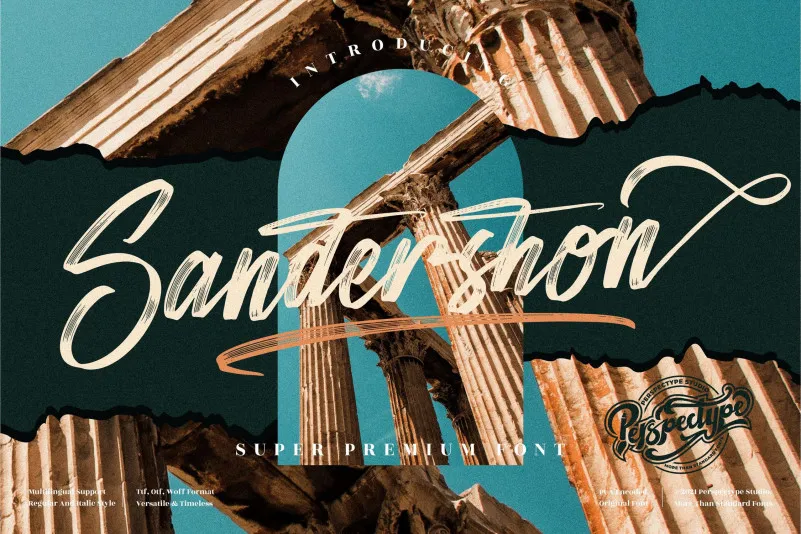
Sandershon Font – Download Grátis
A Sandershon Font é uma escolha ideal para designers que procuram um efeito elegante e moderno no seu trabalho. Ideal para criações personalizadas, como convites de casamento, cartões de agradecimento, rótulos de embalagens, logos e carteirinhas de endereço, ela se destaca por sua caligrafia fortemente decorada e seu estilo distintivo. Esta fonte é especialmente adequada para designers gráficos que buscam um elemento único em seus trabalhos. Ela também oferece acesso a todos os gílitos e swashes de forma fácil e conveniente, graças à sua codificação PUA. A Sandershon Font da perspectype é uma excelente opção para adicionar personalidade a qualquer projeto gráfico, sem sacrificar facilidade no uso.